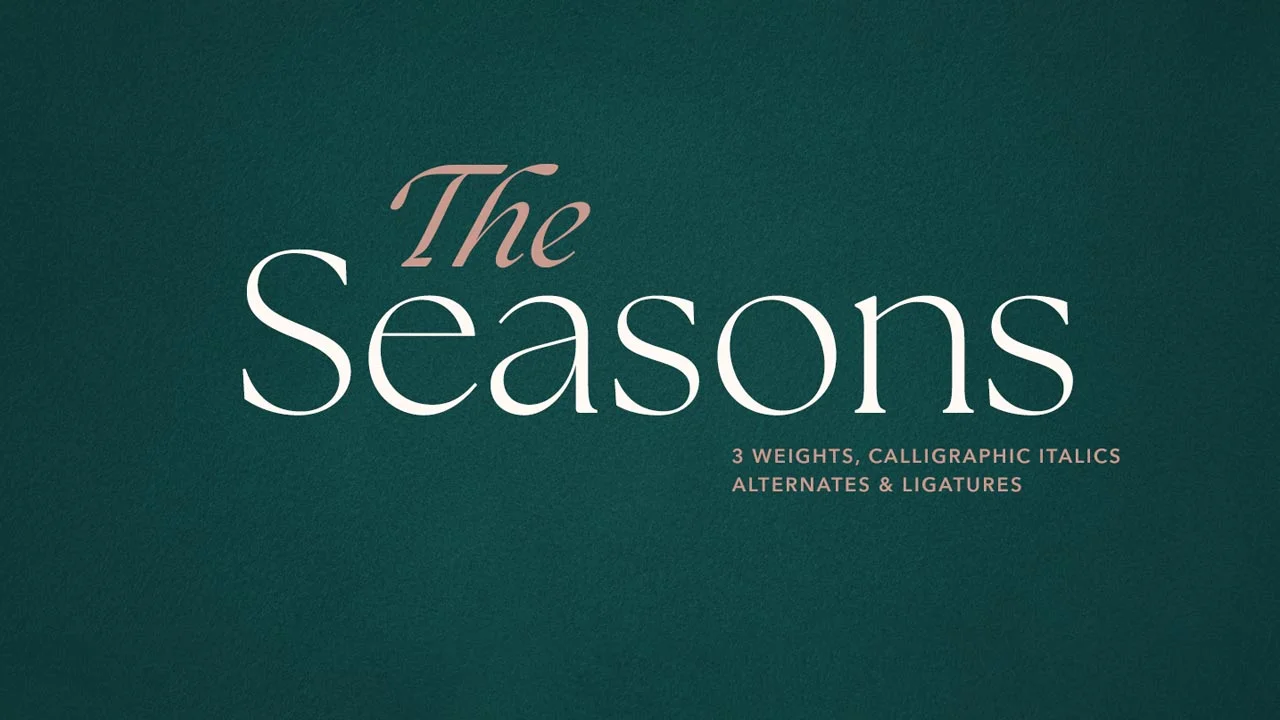
Font việt Hóa Font The Seasons
FONT THE SEASONS – BỘ SƯU TẬP FONT NGHỆ THUẬT THEO MÙA ĐẲNG CẤP
Giới Thiệu Font The Seasons
Font The Seasons là bộ sưu tập font chữ nghệ thuật cao cấp được thiết kế theo đặc trưng của 4 mùa trong năm: Xuân – Hạ – Thu – Đông. Mỗi font chữ trong bộ sưu tập mang đậm tinh thần của từng mùa, giúp truyền tải cảm xúc và phong cách thiết kế độc đáo.
Đặc Điểm Nổi Bật
✅ 4 Font Chữ Độc Đáo Theo Mùa:
• Spring Blossom: Nét chữ mềm mại với họa tiết hoa lá, phù hợp thiết kế mùa xuân
• Summer Vibes: Font năng động, tươi sáng với hiệu ứng ánh nắng
• Autumn Leaves: Chất liệu rustic, phong cách vintage với tông màu cam nâu
• Winter Frost: Nét chữ sắc lạnh, hiệu ứng tuyết phủ
✅ Tích hợp 100+ Glyph đặc biệt: Hoa, lá, bông tuyết, ánh nắng…
✅ Tối ưu cho tiếng Việt: Hỗ trợ đầy đủ dấu, đa nền tảng
✅ Hiệu ứng theo mùa: Ánh kim (hè), texture gỗ (thu), tuyết rơi (đông)
️ Ứng Dụng
✔️ Thiết kế lịch, thiệp mời theo mùa
✔️ Banner quảng cáo thời vụ (Tết, Giáng sinh, Back to School)
✔️ Bao bì sản phẩm theo mùa (trà hoa, kem mùa hè, đồ uống mùa đông)
✔️ Social media theo trend thời tiết
“The Seasons – Bộ font chữ biến hóa theo nhịp thời gian!”